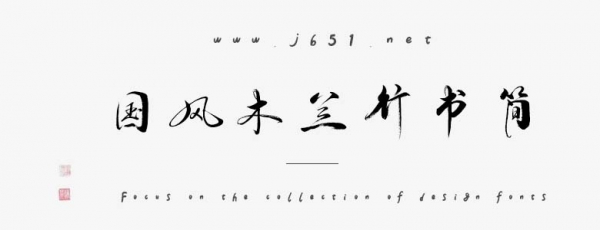
國(guó)風(fēng)木蘭行書(shū)簡(jiǎn)是一款不錯(cuò)的藝術(shù)字體,字體筆觸略細(xì),具有很好的視覺(jué)感,適合應(yīng)用于藝術(shù)設(shè)計(jì)、平面宣傳設(shè)計(jì)、網(wǎng)頁(yè)設(shè)計(jì),書(shū)法字帖等領(lǐng)域,需要的朋友可以前來(lái)本站下載。